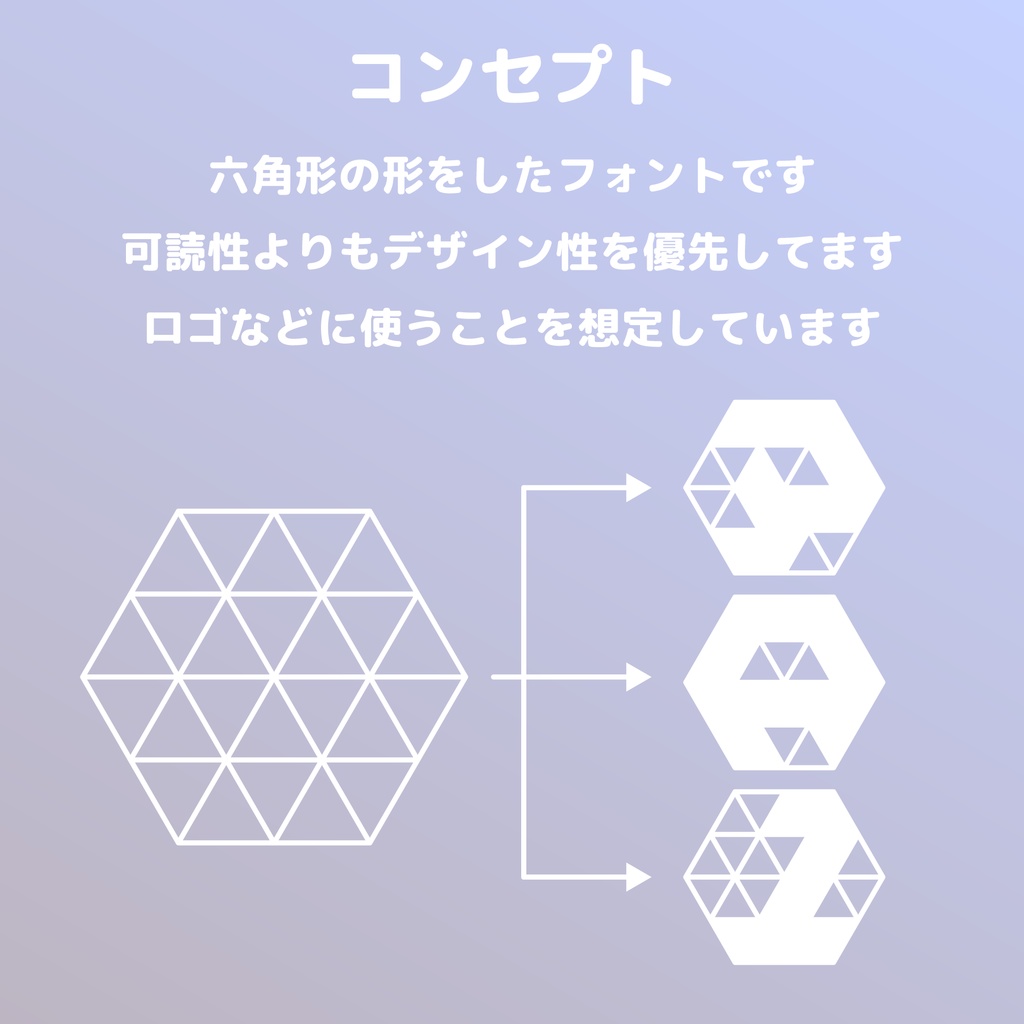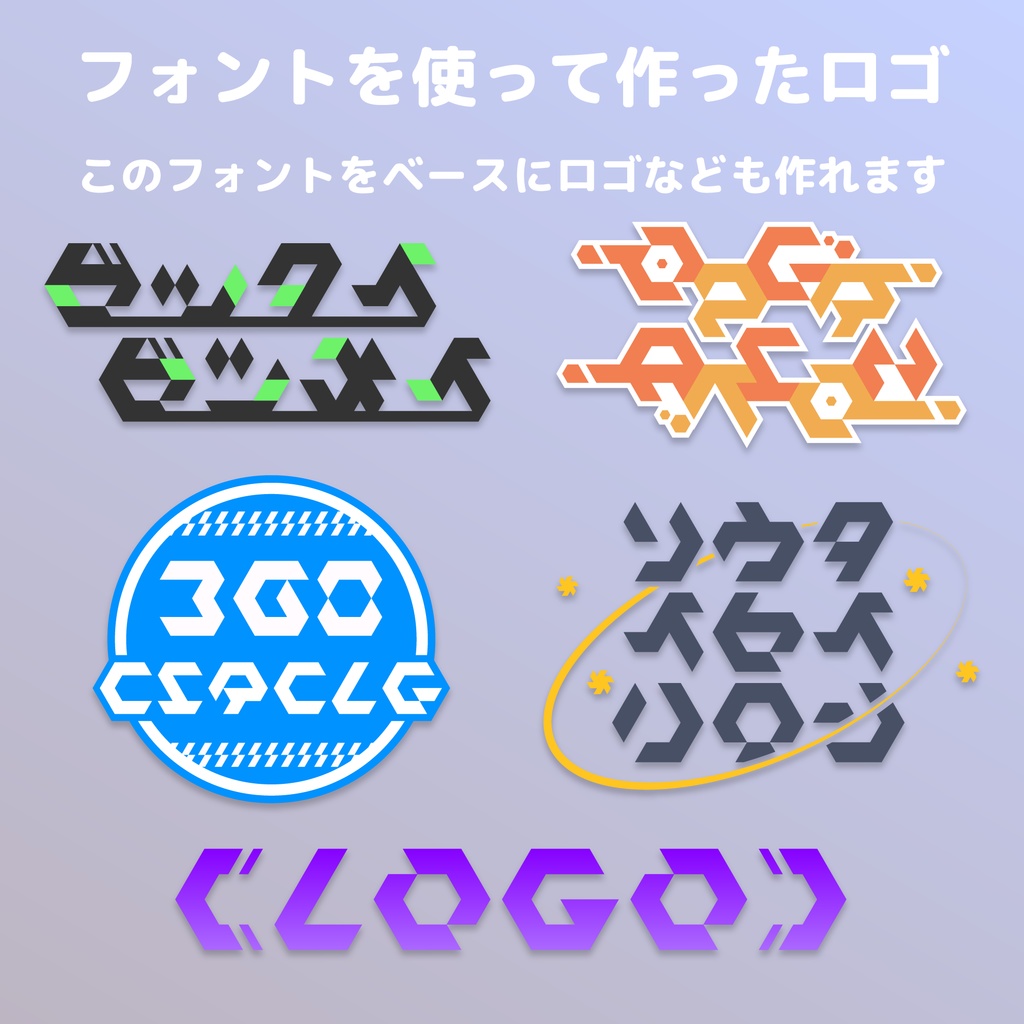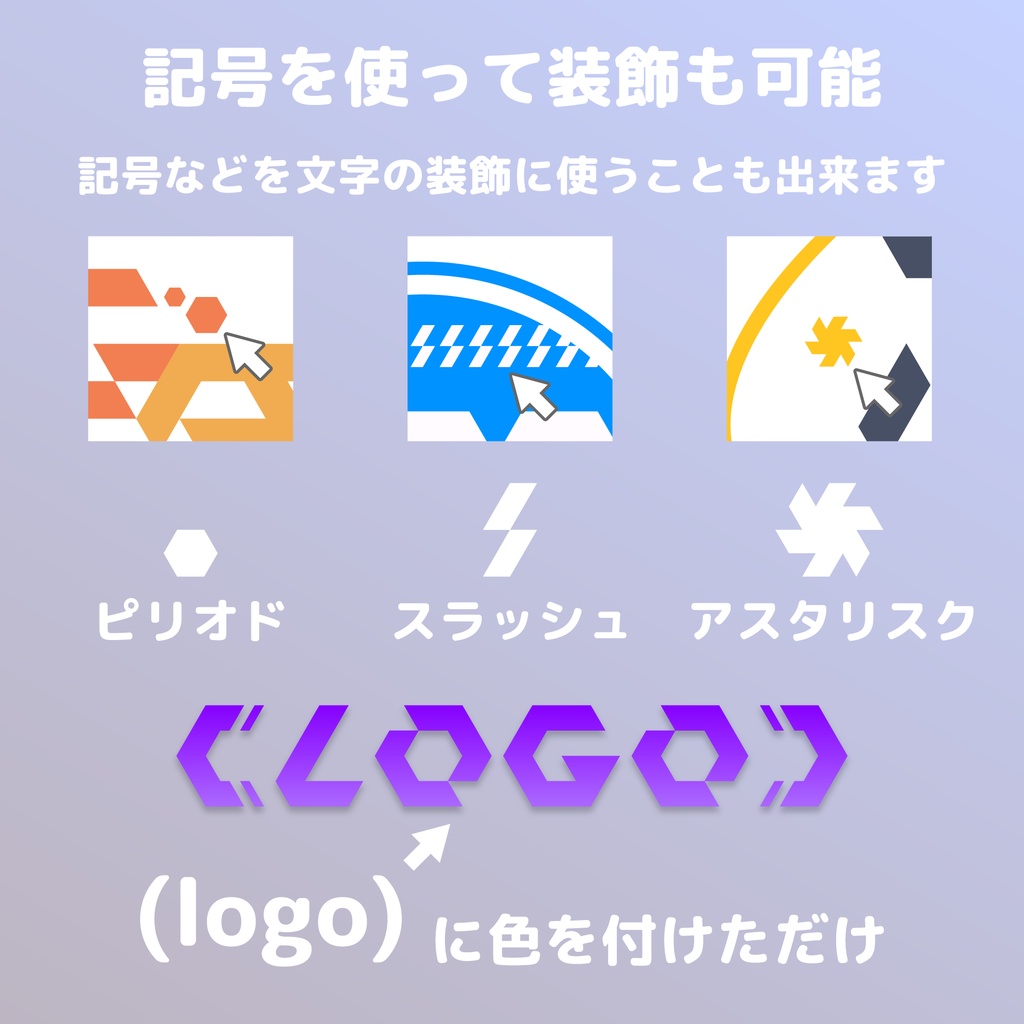
【フリーフォント】ヘキサメテオ
六角形の形をしたフリーフォントです。可読性よりもデザイン性を優先して作りました。 ロゴなどに使うことを想定しています。 英数字だけではなく、カタカナも収録しているので日本語のロゴでも使いやすいです。 また、記号もいくつか収録しているのでそれらをロゴの装飾として使うことも可能です。 個人・商用どちらでも利用可能です。 詳細は同封されている「hexameteor-readme.txt」をご確認ください。 銭 投げ銭枠はありますが、フォントファイルは同一のものです。 ■収録文字 カタカナ・英数字(英字は全て大文字のみ)・一部記号 145文字収録 OpenTypeフォント ■注意事項 ・使用する際は同封されている「hexameteor-readme.txt」をよく読み利用してください。 ・フォントのインストール等の技術的なサポートはいたしません。 ・フォントを使用して発生したと思われる如何なる問題についても、作者は責任を負わないものとします。 ・こちらのフォントは Fontlab 7 を利用して作られています。 ・使用する際作者への報告は不要です。ただ、報告されるととても喜びます。 ■お問い合わせ mail: orange634nty@gmail.com twitter: @orange634nty